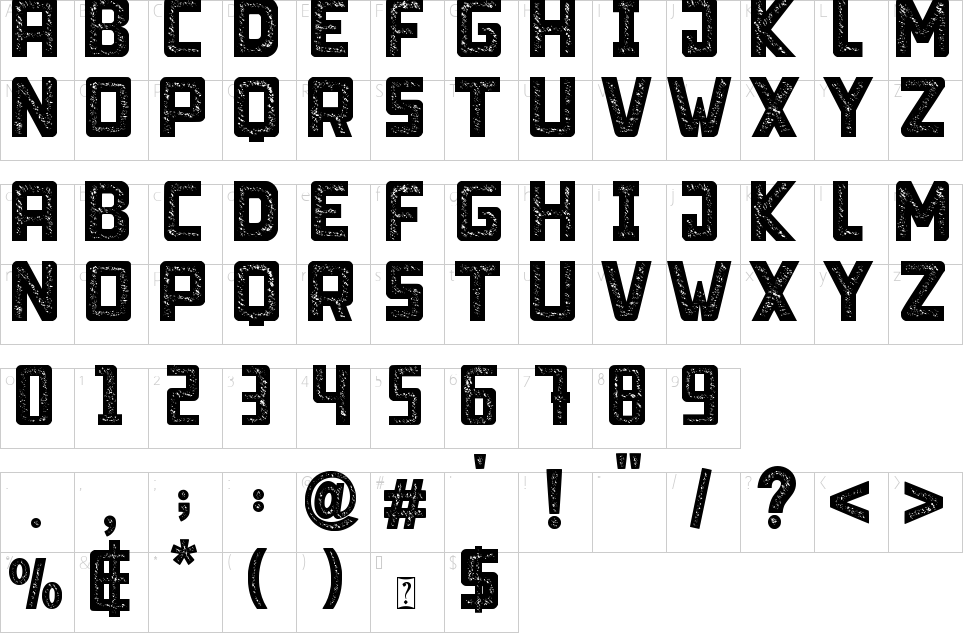
Descubra a beleza das linhas do Limit Breaking Font para seus projetos digitais. Esta elegante fonte foi desenhada por Thomas Aradea e já foi instalada nas telas de muitos criadores de conteúdo. Com uma arquitetura minimalista que destaca o texto em um estilo único, ela é perfeita para criar designs atraentes e modernos, seja para aplicativos, sites ou qualquer projeto visual onde você precise de uma escolha de letra excepcional. Seja qual for seu propósito, se você está procurando por uma fonte grata que não comprometa sua criatividade, o Limit Breaking pode ser exatamente o que você precisa. Descubra agora e transforme seus projetos digitais no topo do design.